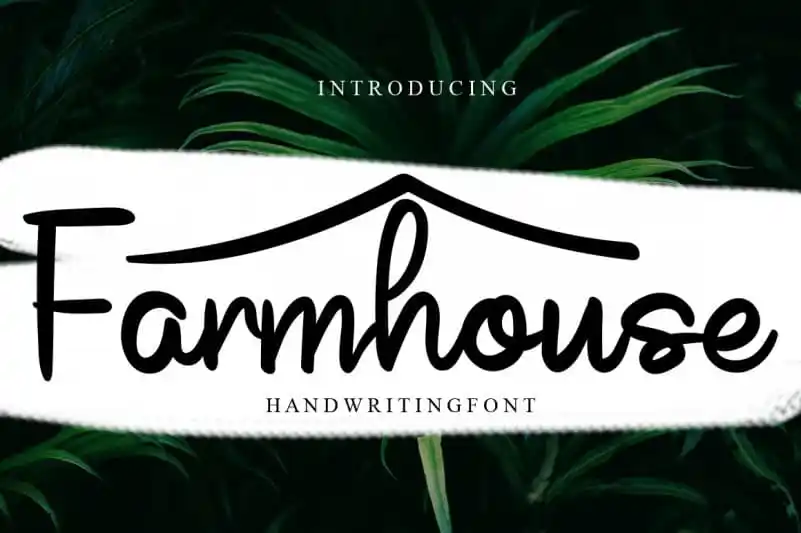
Farmhouse Script Font – Download Grátis
A Farmhouse Script Font é uma elegante tipografia frondosa que transmite delicadeza e sofisticação com um toque de modernidade. Suas linhas finas e lisas criam um visual limpo e minimalista, fazendo dela a escolha perfeita para qualquer design. A tranquilidade e conforto da fonte complementam os ambientes rústicos e casuais sem perder sua elegância. Ideal para designers que buscam uma fonte frondosa para ilustrações de receitas casuais, recados pessoais ou até mesmo como elemento de decoração em lojas de artesanato. Esse estilo caseiro é perfeito para um design vintage que se encaixa na cultura da casa e do campo. Seja para adicionar um toque autêntico a sua criação digital, a Farmhouse Script Font oferece uma maneira única de expressar sentimentos e ideias de uma maneira suave e envolvente. Com seu designer experiente Levincreative, você pode estar certo de que esta fonte irá manter o estilo fresco e acolhedor característico da farmecheia na sua próxima produção visual.